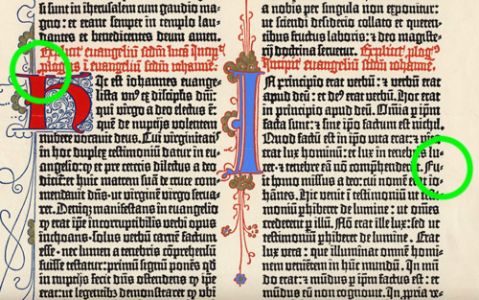
Die Schattierung – die ich als echten Druckfehler kenne – hatte ich übrigens nicht gemeint mit „Druckrelief“, sondern die verfahrensbedingte Verdichtung des Bedruckstoffes an den bedruckten Stellen, natürlich auch den Quetschrand, der durch seine Kontrasterhöhung Buchdruckschriften bis heute so gut lesbar macht. Hierdurch entsteht auch die einzigartige Anmutung von Handdrucken, die im Laufe der Jahrhunderte interessante Besonderheiten vorzuweisen hat. Man muss die Inkunabeln von Bodoni schon einmal im Original gesehen haben, um zu verstehen, wie er seine Schriften gemeint hat.
Die „Lebendigkeit der Lettern“, wie wir sie im Handsatz und bedingt auch im Maschinensatz finden, dürfte eine der Eigenschaften dieses Druckverfahrens sein, die im industriellen Bereich, also dem heutigen Offset-, Tief- und auch Flexodruck (!) für immer verloren gegangen sind. Wir drucken heute mit 8 Metern pro Sekunde, sowohl im Zeitungs- als auch im Illustrationsbereich, im Tiefdruck mit derzeit max. 4,20 m breiten Zylindern. Da hat natürlich die typografische Qualität in dieser Hinsicht durchaus gelitten, aber an anderen Stellen konnte sie – auch im Mengen-, Buch oder Werksatz – gesteigert werden.
Ein Experiment, die Individualität des Buchstabenrandes durch PostScript-Algorithmen zu imitieren, ist übrigens die „Beowulf“, deren Outlines beim Rippen jeweils leicht modifiziert wurden. Hat sich aber nicht durchgesetzt, und die Ergebnisse waren auch nicht wirklich überzeugend. Da fehlt dann doch die haptische Anmutung des spezifischen Materials.
Ich hatte den „Mehrzeilensetzer“, von dem „Psocopterus“ sprach, vergessen zu erwähnen. Dies ist eine Eigenschaft von InDesign oder eben TeX, die erheblich zur Verbesserung des Blocksatzes beiträgt. In der Newsgroup de.comp.tex.dtp hatten wir kürzlich eine Diskussion über die Blocksatzqualität aktueller Applikationen, auch im Vergleich zu MS Word. Ich persönlich bin von dieser Funktion über alles angetan, sie bringt auf Anhieb ohne größere Korrekturen akzeptable Blocksatzqualität. Im Gegensatz zum Hand-, Maschinen oder Fotosatz werden für die Berechnung der Trennungen nicht nur die aktuelle Zeile, sondern auch bis zu 3 Zeilen darüber und darunter berüclsichtigt.
Nächstes Kriterium ist das optische Kerning von InDesign, das TeX schwerlich vorweisen dürfte. Das entspricht vielleicht noch em ehesten der ursprünglichen Fragestellung nach den alten Ausschießregeln, da hier neben den Kerningwerten auch das „Fleisch“ innerhalb der Buchstaben zu berücksichtigen versucht wird. Hier ein Beispiel, was dieser Automatismus auf Anhieb im Versalausgleich bringt:
Von oben nach unten:
1. metrischer Ausgleich, Laufweite 0
2. metrischer Ausgleich, Laufweite 200
3. optischer Ausgleich, Laufweite 200
4. optischer Ausgleich, Laufweite 200, manuell nachgebessert
Zum historisch benutzten Randausgleich: Eine Replik der 42-zeiligen Bibel vom Gutenbergmuseum zeigt, dass der Randausgleich hier tatsächlich an beiden Rändern vorgenommen wurde:
Und hier noch ein Bild, in dem gut zu sehen ist, an wie vielen Stellen metrisches Kerning und Randausgleich schon ohne optisches Kerning zum Einsatz kommen (Berthold):
Der Vergleich der Satzqualität über die Jahrhunderte wäre sicherlich einmal ein Thema für eine Diplomarbeit – aber wahrscheinlich gibt’s da auch schon etwas. Vielleicht kennt hier jemand Literatur?